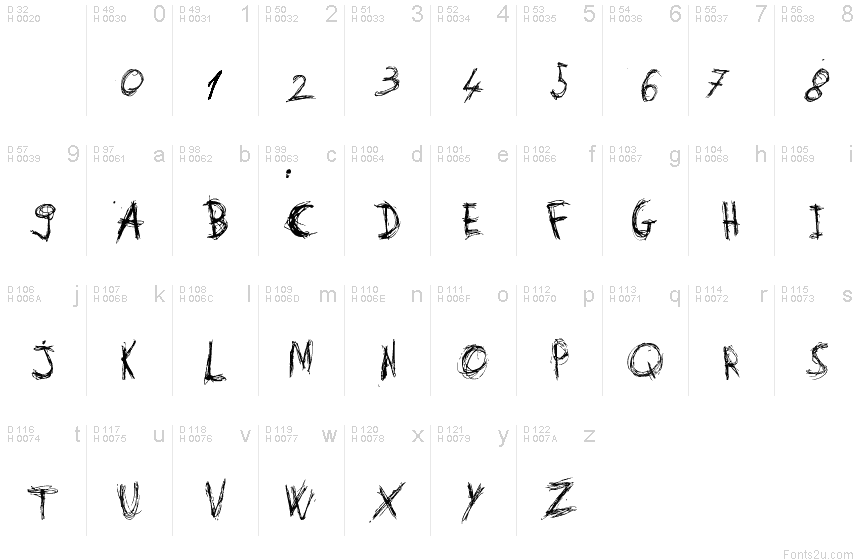
Scratchy to darmowy krój pisma typu „trash” w wielkich literach, o surowym, „pociętym” wyglądzie. Litery sprawiają wrażenie wydrapanych szybkimi czarnymi pociągnięciami, przekreślonymi pętlami i postrzępionymi znakami, przez co cały alfabet wygląda bardziej jak nabazgrany plakat niż uporządkowana typografia.
Dzięki temu ten darmowy font naturalnie odnajduje się na punkowych ulotkach, okładkach zinów, logotypach zespołów, horrorowych planszach tytułowych i surowych nagłówkach redakcyjnych. Sprawdza się też w krótkich cytatach, początkach rozdziałów i monogramach, gdzie niespokojne linie i niechlujne nachodzenia na siebie najlepiej sprawdzają się w krótkich, wyrazistych projektach.